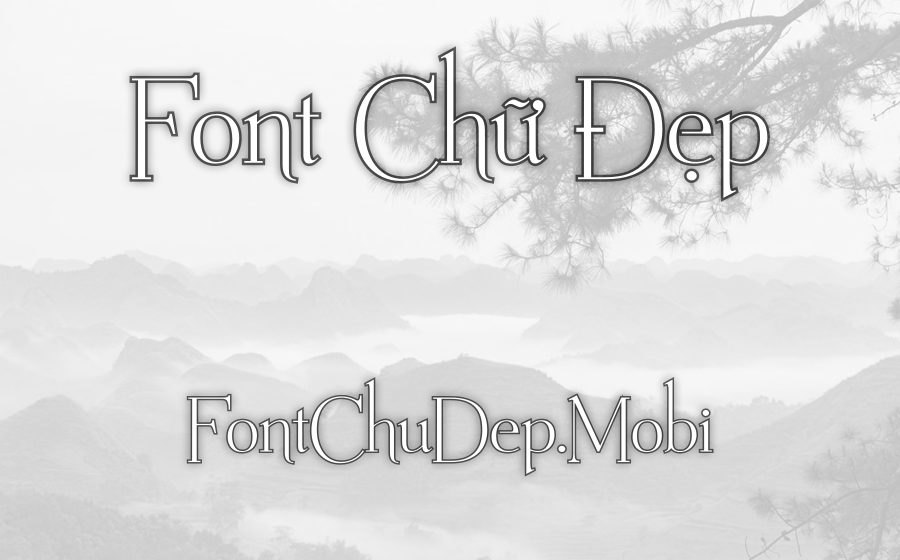
Font UVF Mussica Swash Việt Hóa
UVF Mussica Swash
Mussica Swash là một kiểu chữ trang trí đặc biệt mà tôi đã có cơ hội trải nghiệm và cảm nhận. Được hình thành dưới bàn tay tài hoa của nhà thiết kế Manuel Eduardo Corradine vào năm 2009, font chữ này gây ấn tượng mạnh mẽ nhờ vào đường nét thanh mảnh lồng ghép với những đường cong trau chuốt, tạo nên vẻ đẹp vừa thanh lịch vừa mang đậm nét cá tính. Sự tinh tế và tính nghệ thuật của Mussica Swash đã chinh phục ngay cả những người có gu thẩm mỹ khắt khe nhất.
Một điểm cộng lớn của Mussica Swash chính là khả năng đáp ứng nhu cầu sử dụng của người Việt Nam, nhờ vào phiên bản Việt hóa được thực hiện chỉn chu. Font chữ này là sự lựa chọn hoàn hảo cho các dự án sáng tạo đòi hỏi tính thẩm mỹ cao như thiệp mời, tiêu đề, logo hay các tác phẩm nghệ thuật. Đặc biệt, Mussica Swash toả sáng trong lĩnh vực sự kiện, nơi nó có thể được áp dụng một cách độc đáo trong các dịp lễ hội, lễ cưới cũng như các sự kiện văn hóa đặc sắc.
Không chỉ dừng lại ở đó, Mussica Swash còn thể hiện sự linh hoạt khi phù hợp với nhiều ngành nghề khác như quảng cáo, thiết kế thiệp cưới và nghệ thuật trang trí. Font này thực sự là một sự lựa chọn đáng giá cho những ai đang tìm kiếm một phong cách độc đáo và tinh tế. Nếu bạn chưa từng thử qua, tôi khuyên bạn hãy trải nghiệm ngay trên FontChuDep.mobi, nơi bạn có thể khám phá tất cả những nét đẹp mà Mussica Swash mang lại.